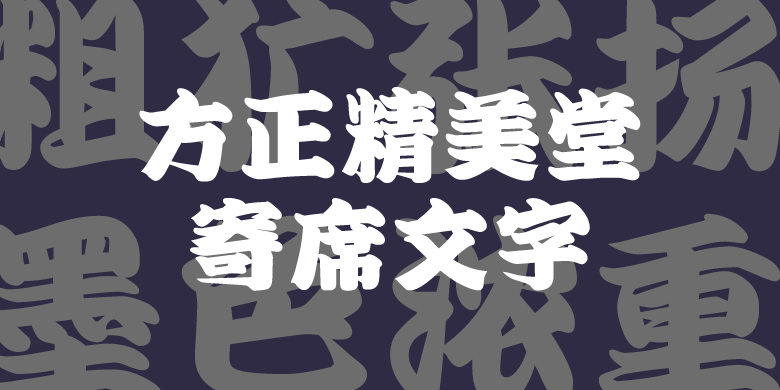
方正精美堂寄席文字
日本精美堂
创意字体
方正精美堂寄席文字是方正电子于2025年从日本引进的一款创意字体,该字体是日本江户时代流行的特殊书法字体,具有粗犷张扬的笔法特征,笔势方向整体笔画向右上方倾斜,‌墨色浓重而且笔画粗壮,常见于寄席演艺(传统落语表演)和新年祈福,被视为吉祥文字。主要用于海报、传单和千社札(姓名贴纸)等。